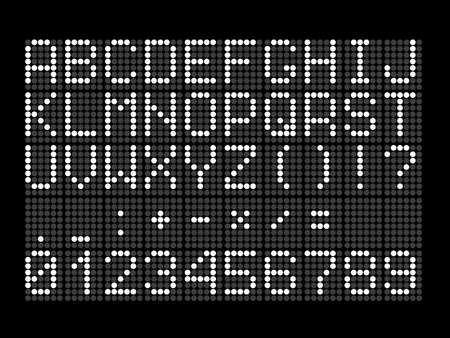
ドット 文字 フォント
KHドットフォントは、平木敬太郎氏がデザインしたフォントを、自家製フォント工房が TrueType フォント化したものです。 フォントデータに含まれる文字グリフの著作権は.
ドット 文字 フォント. 2.「書式(O)」→「フォント(F)」 でフォントを開き、フォント名を「MS ゴシック」にして、スタイルを標準にして、サイズを12にします。 3.メモ帳に、ドット字にしたい文字(文)を書きます。. ドラクエ風のフォントを使うときの小技としては、文節ごとに間隔を開けると雰囲気がバッチリ出ます。 間隔を開けるとドラクエ感が増します! ドラクエといえば、やっぱり黒背景に白文字!それに白い枠なんかつけ. 5×7のマス目で書いたフォントのため 雰囲気でしか書いてないのに、 文章の中ではなぜか読めちゃうという不思議なフォントです。 収録文字などは画像で。.
Adobe Fonts はサブスクリプション形式のフォントライブラリです。世界の優れたフォントメーカーと提携して美しいフォントを提供します。お気に入りのフォントをライブラリから選択して、アドビのサービスを使用してWebサイトでホストしたり、デスクトップアプリケーション上で使用するため. 美咲フォントは 8×8 ドットの日本語ビットマップフォントです。 jis 第一・第二水準をサポートしています。 一部の記号を除いた全ての文字は 7×7 ドットの範囲に収まっているため、文字同士を隣接させても行間・字間が確保できます。. 標準表示(罫線同じ) 10行 (330文字) 7行 (154文字) 5行 (80文字) 4行 (52文字) 3行 (30文字).
美咲フォントは 8×8 ドットの日本語ビットマップフォントです。 jis 第一・第二水準をサポートしています。 一部の記号を除いた全ての文字は 7×7 ドットの範囲に収まっているため、 文字同士を隣接させても行間・字間が確保できます。 サンプル画像. 異なる文字同士で字形が一致している場合があります。 所謂半角フォントは美咲フォント同梱の 4×8 ドットフォントを 横 3 ドットにカットしたものです。 隣り合う文字が接触してしまいますがご了承ください。 実用性極めて低し。 制作履歴. 形式は Truetype ですが、実質的にはドットフォントです。 導入済チェック.
19年5月16日 Windows 10 で画面がぼやけるのは何故? 原因と解決方法を紹介. デザインのちょっとしたアクセントやゲームの制作に使えそうな、ファミコン風フォントを3つ紹介します。全てJIS第二水準まで対応しているというのも大きなポイントです。 美咲フォント(8x8) 一部の記号は8x8ドットですが、それ以外は全て7x7ドットで作られているという恐ろしいフォント. Adobe Photoshopで、ドット文字を作る方法を解説しています。 キレイで、多種多様のフォントが使えるようになった現在、あえての「ドット文字」が.